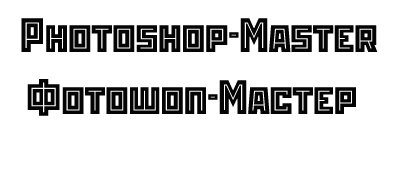
Шрифт Красивый создатель шрифта спасибо Но извини за придирание :( корочь Цифровой шрифт осталь=ные красивей :*(
Напоминает шрифт с советских плакатов)